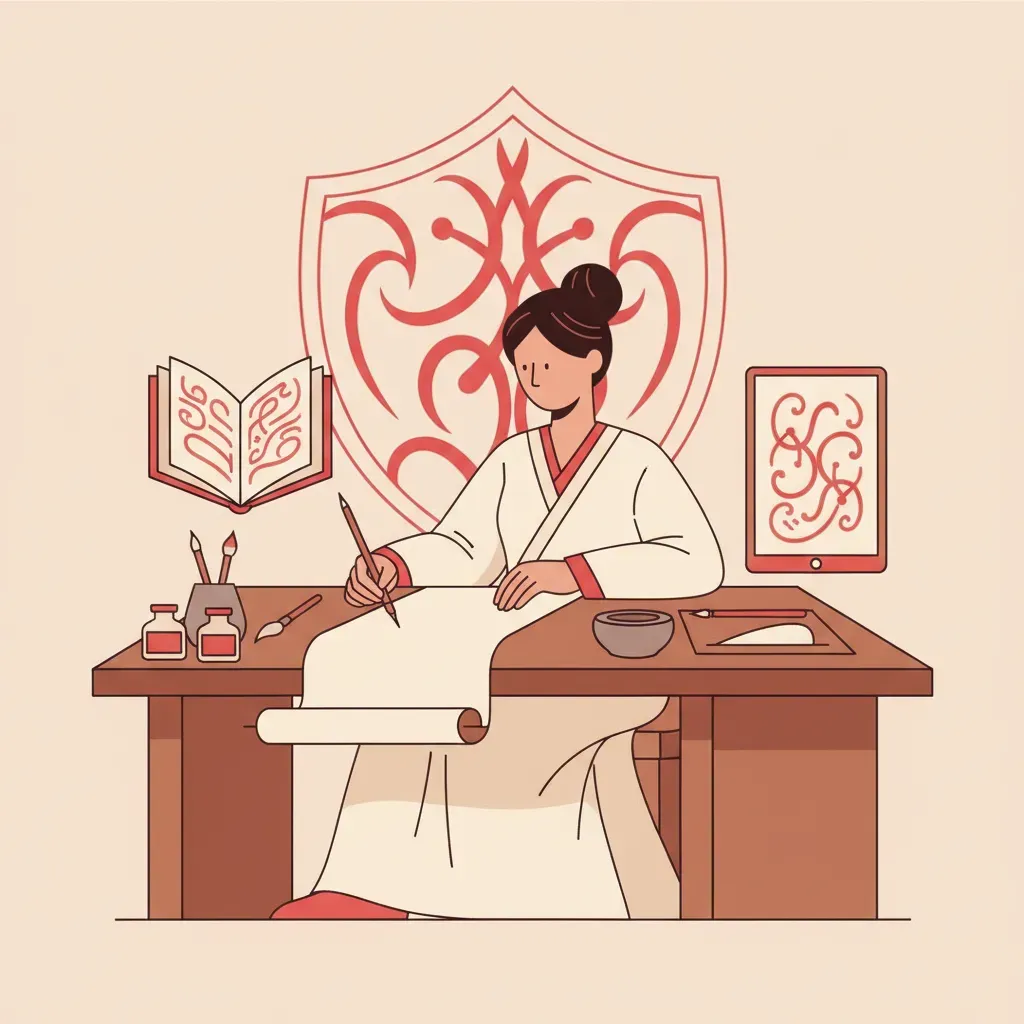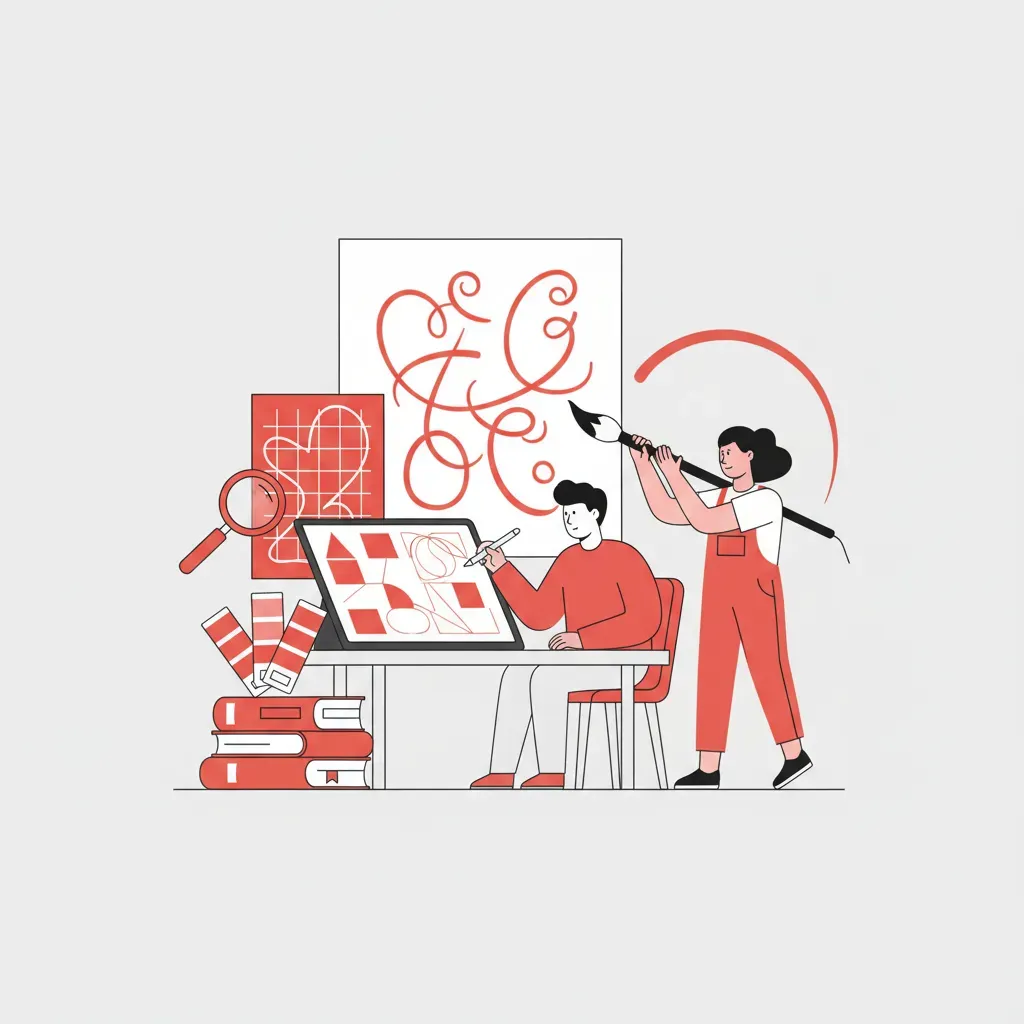
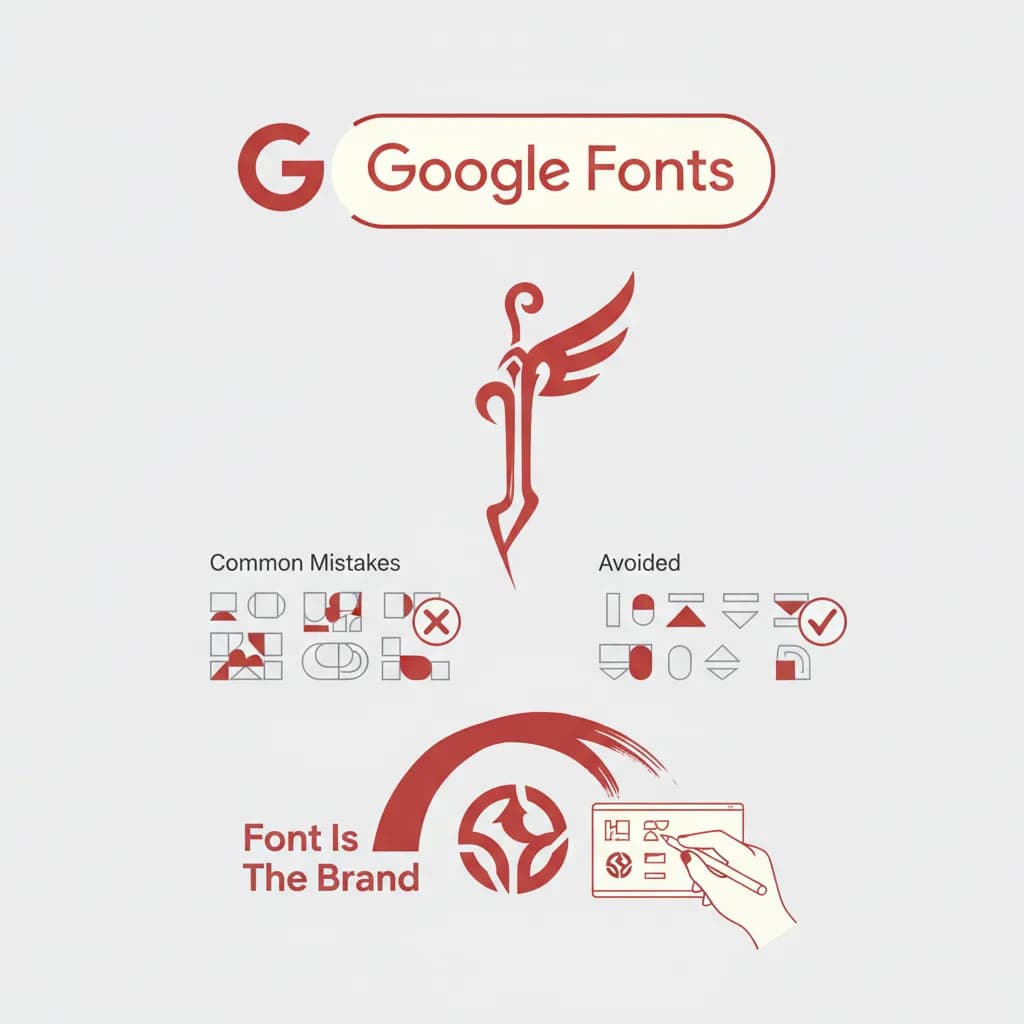
הפונט שבחרת לכותרת האתר שלך מספר סיפור – לפני שהלקוח קרא מילה אחת. בעולם שבו כל מותג מתחרה על שניות של תשומת לב, בחירת גוגל פונט עברי נכון היא לא החלטה אסתטית – היא החלטה עסקית. Google Fonts היא ספרייה חינמית הכוללת מגוון רחב של גופנים בשפות שונות, ובין הפונטים העבריים הזמינים בה תמצאו כלים שיכולים לשנות את האופן שבו הקהל שלכם תופס את המותג. אבל הבחירה הנכונה דורשת הבנה – לא רק של הסגנון, אלא של האסטרטגיה שמאחוריו.
גוגל פונט עברי: הנשק המיתוגי שהמותג שלך חיכה לו
טיפוגרפיה עברית היא שדה מורכב יותר מאנגלית – כיוון הכתיבה, אופי האותיות, והמשקל הוויזואלי שלהן שונים לחלוטין. כשמותג בוחר פונט עברי, הוא מגדיר את הטון הרגשי של כל תקשורת עתידית עם הלקוח. פונט כבד ומרובע ישדר אמינות ויציבות. פונט קליגרפי ישדר חום ואישיות. פונט גיאומטרי נקי ישדר חדשנות וטכנולוגיה.
מחקרי UX מצביעים על כך שהטיפוגרפיה משפיעה על תפיסת האמינות של מותג לפני שהצרכן מעבד את תוכן הטקסט עצמו. כלומר – הפונט עובד על הקורא ברמה לא-מודעת, ויוצר רושם ראשוני שקשה מאוד לשנות לאחר מכן. זו בדיוק הסיבה שבחירת פונט עברי נכון היא החלטה שצריכה להיות מובילה על ידי אסטרטגיה מיתוגית – לא רק על ידי טעם אישי.
Google Fonts הוא אתר אינטרנט בבעלות חברת גוגל המשמש כספרייה חינמית של גופנים בשפות שונות. הפונטים העבריים בספרייה זו עברו תהליכי עיצוב מקצועיים ומתאימים לשימוש בסביבות דיגיטליות מגוונות – מאתרי אינטרנט ועד אפליקציות.
כשבוחרים פונט עברי ממאגר Google Fonts, חשוב להבין שהבחירה אינה רק ויזואלית – היא גם טכנית. הפונטים הפתוחים של גוגל מאפשרים שילוב קל בכל פלטפורמה, מה שמעניק עקביות מיתוגית מלאה בין האתר, המצגות והחומרים השיווקיים. לעיון נוסף בנושא התאמת פונטים – מדריך מלא עם דוגמאות יעזור לכם לבחור שילובים נכונים.
בחירת פונט עברי למיתוג היא תהליך שיטתי שדורש חשיבה מקדימה. להלן תהליך מובנה שמעצבים מקצועיים משתמשים בו:
שלב 1: הגדרת אישיות המותג
לפני שנכנסים ל-Google Fonts, רשמו 3-5 תכונות שאתם רוצים שהמותג ישדר. "אמין ומקצועי" ידריך אתכם לכיוון שונה מ"צעיר ומשחקי".
שלב 2: בחינת קהל היעד
גיל, תרבות ורמת פורמליות של קהל היעד משפיעים ישירות על בחירת הפונט. מותג המיועד לקהל בגיל 60+ יצטרך פונט קריא בגדלים גדולים יותר. מותג לדור Z יכול להרשות לעצמו פונט ניסיוני יותר.
שלב 3: בחינת הקשר השימוש
האם הפונט ישמש בעיקר לכותרות? לגוף טקסט? לממשק דיגיטלי? לחומרי הדפסה? כל הקשר דורש תכונות שונות מהפונט. פונט כותרות יכול להיות דרמטי ובולט, בעוד פונט גוף חייב להיות קריא ונוח.
שלב 4: בדיקת תאימות טכנית
ודאו שהפונט תומך בכל התווים העבריים שתצטרכו, כולל ניקוד אם רלוונטי. בדקו שהפונט נטען מהר ולא פוגע בביצועי האתר. לפרטים נוספים על פונט כותרות שמעצים כל שורה בעיצוב עברי – ראו את המדריך המקצועי.
שלב 5: בדיקת שילוב פונטים
רוב המותגים משתמשים בשתי משפחות פונטים – אחת לכותרות ואחת לגוף. ודאו שהשילוב יוצר היררכיה ויזואלית ברורה ולא מתחרה בעצמה.
לאחר שבחרתם את הפונט, השלב הבא הוא שילובו נכון בכל נקודות המגע של המותג. הנה העקרונות שמבדילים בין מיתוג בינוני למיתוג מצוין:
עקביות מעל הכל. הפונט שבחרתם חייב להופיע באותה צורה בכל המדיומים – אתר, כרטיסי ביקור, מצגות, ניירות מכתבים. כשמותג משנה פונטים בין פלטפורמות, הוא שולח מסר של חוסר מקצועיות. לעיון בנושא גופנים מומלצים שמחזקים את המיתוג העסקי – תמצאו שם בחירות מוכחות שעובדות.
היררכיה ויזואלית ברורה. השתמשו במשקלים שונים של אותה משפחת פונטים כדי ליצור היררכיה. כותרת ראשית – Bold, כותרת משנה – Medium, גוף טקסט – Regular. זה יוצר עין מנוחה ומדריך את הקורא בצורה טבעית.
גודל ורווח שורות. בעברית, בגלל אופי האותיות, נדרש לרוב רווח שורות גדול יותר מאנגלית – לפחות 1.6-1.8 בגוף טקסט. זה משפר קריאות ומעניק לעיצוב תחושת מרחב ואיכות.
סוג מותג פונט מומלץ הסיבה טכנולוגיה / סטארטאפ Heebo / Rubik מודרני, קריא, ניטרלי מסעדה / מזון Amatic SC / כתב יד חם, אישי, ביתי שירותים פיננסיים Alef / David Libre אמין, רציני, מסורתי אופנה / עיצוב Varela Round / פונט ייחודי יצירתי, בולט, בלתי נשכחשימוש בגוגל פונט לא נכון יכול לפגוע במיתוג בצורה משמעותית. אלה הטעויות הנפוצות ביותר שרואים בפרויקטים ישראליים:
טעות 1: טעינת יותר מדי גרסאות של גוגל פונט. כל משקל פונט שמוסיפים מ-Google Fonts מוסיף זמן טעינה לאתר. מעצבים רבים טוענים את כל 9 המשקלים "ליתר ביטחון" – ומקבלים אתר איטי. הכלל הפשוט: טענו רק את המשקלים שתשתמשו בהם בפועל, בדרך כלל 2-3 לכל היותר.
טעות 2: שימוש בגוגל פונט שלא כולל את כל התווים הדרושים. לא כל פונט עברי ב-Google Fonts כולל תמיכה מלאה בניקוד, בתווים מיוחדים או בפסיקים עבריים. לפני אימוץ פונט למיתוג, בדקו שהוא תומך בכל טווח התווים שתצטרכו – כולל מספרים ופיסוק.
טעות 3: שימוש בגוגל פונט ללא fallback מוגדר. כשגוגל פונט לא נטען (בגלל חסימה, בעיית רשת, או הגדרות פרטיות), הדפדפן עובר לפונט ברירת המחדל שלו – ויכול להרוס את כל הממשק. תמיד הגדירו שרשרת fallback: `; color:#374151; line-height:1.75; margin-bottom:1rem; direction:rtl;">טעות 4: בחירת פונט שכולם משתמשים בו. Heebo הוא פונט מצוין – אבל כשכל אתר ישראלי נראה זהה, המיתוג שלכם מאבד ייחודיות. שקלו שילוב של גוגל פונט כבסיס עם פונט מקצועי ייחודי לכותרות, כמו פונט מזרחי שמביא אופי ייחודי ובלתי נשכח לכל עיצוב.
הנה נקודות המפתח שכדאי לזכור:
רעיונות ליישום מיידי: נסו להחליף את פונט הכותרות באתר שלכם לפונט אחד שונה ובדקו את הרושם. צרו שתי גרסאות של כרטיס הביקור שלכם עם פונטים שונים ושאלו לקוחות מה מרגיש יותר נכון. חפשו ב-Google Fonts את הקטגוריה "Hebrew" וסננו לפי סגנון שמתאים לאישיות המותג שלכם.
הפונט הנכון הוא זה שגורם ללקוחות שלכם להרגיש "זה בדיוק המותג שאני מחפש" – בשנייה הראשונה, לפני שקראו מילה.